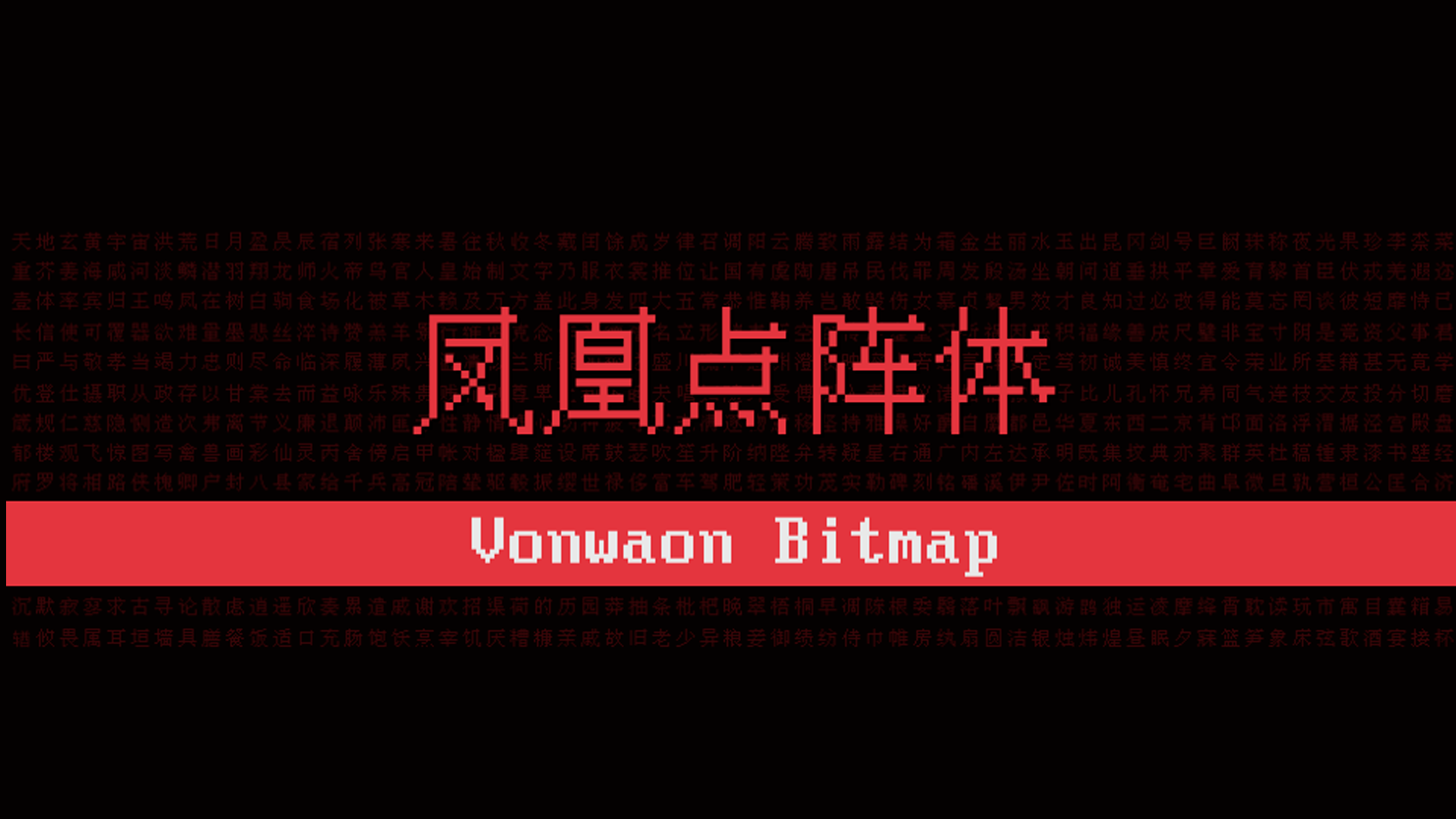
凤凰点阵体字模基于开源项目 BitmapFont (https://github.com/aguegu/BitmapFont),针对汉字与非汉字、不同字号、字体之间的搭配使用进行了优化。
压缩包中有 12px 和 16px 两个版本的字体(对应 9pt 和 12pt),这是它们各自所使用的基准字模的像素高度。字号设置为对应尺寸的整数倍时,TTF 字体的显示效果最佳。
凤凰点阵体共包含 7543 个字符,其中汉字 6763 个。如果你非常在乎文件大小,可以使用 Lite 版,共包含 4041 个字符,其中汉字 3755 个(省略了较少使用的二级汉字)。Lite 版不包含日文假名、希腊字母、俄文字母、拼音、注音符号、制表字符、以及序号字符。
本字体有两个版本
Lite 版所支持的汉字数量约为完整版的一半,不包含特殊字符。